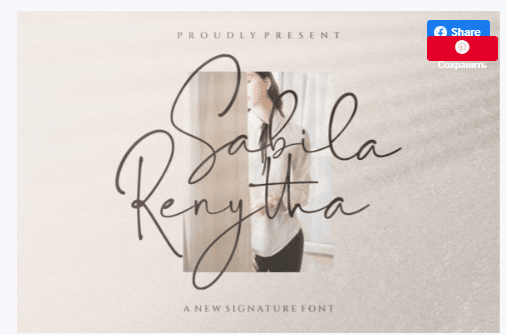
Sabila Renytha Font
Sabila Renytha - стильный и нежный шрифт. У него чистая, тонкая и гладкая атмосфера, и он станет хитом для любого дизайна, к которому вы хотите добавить его.